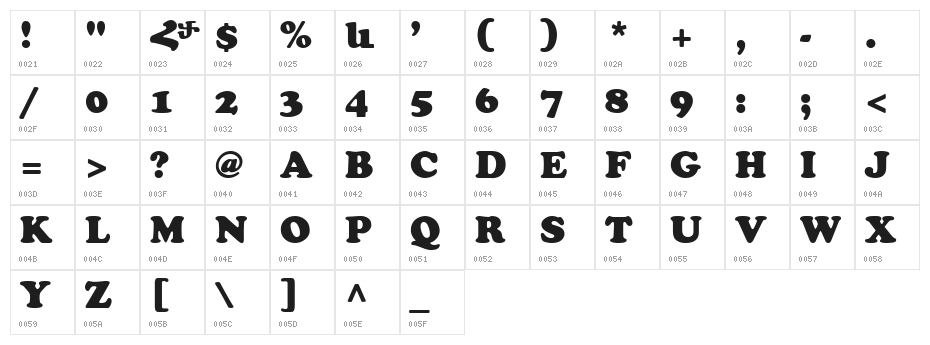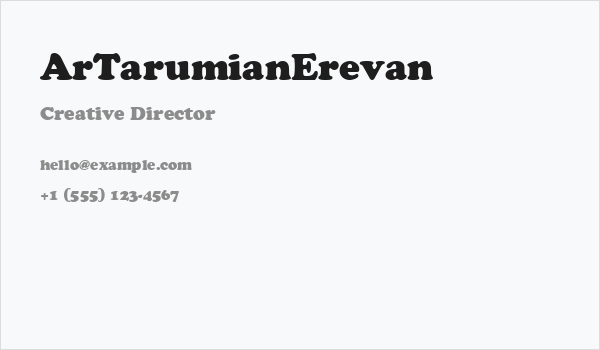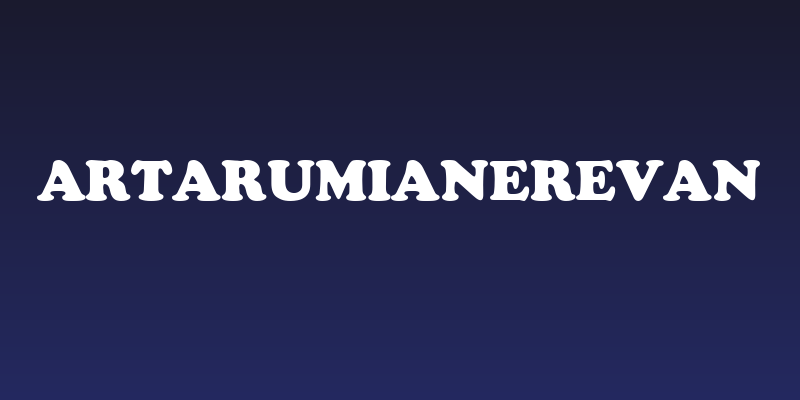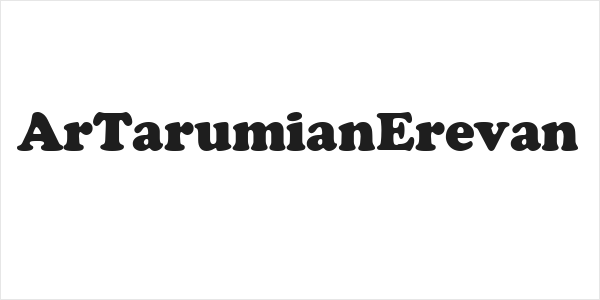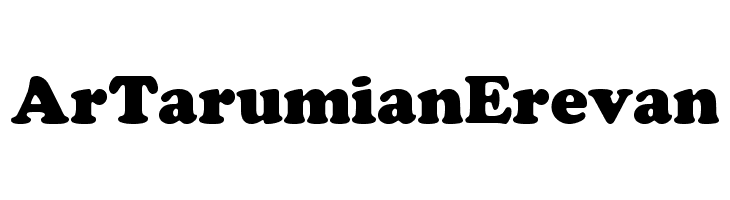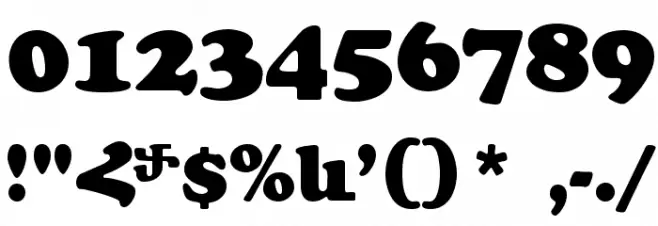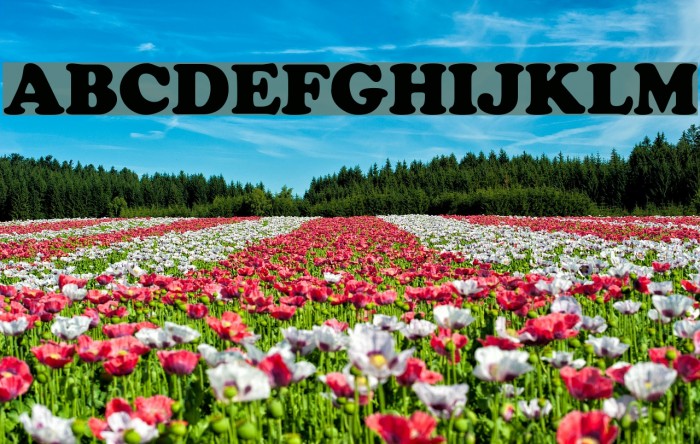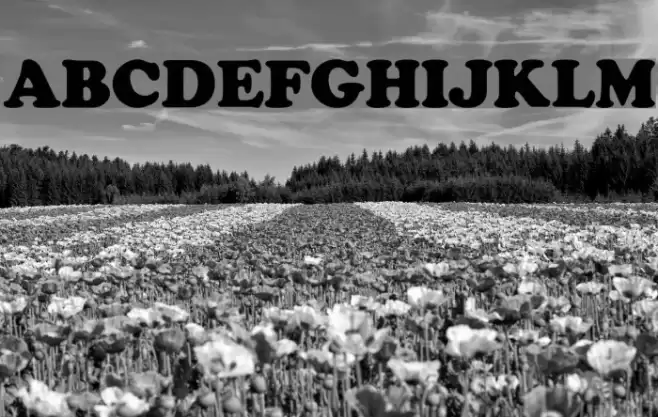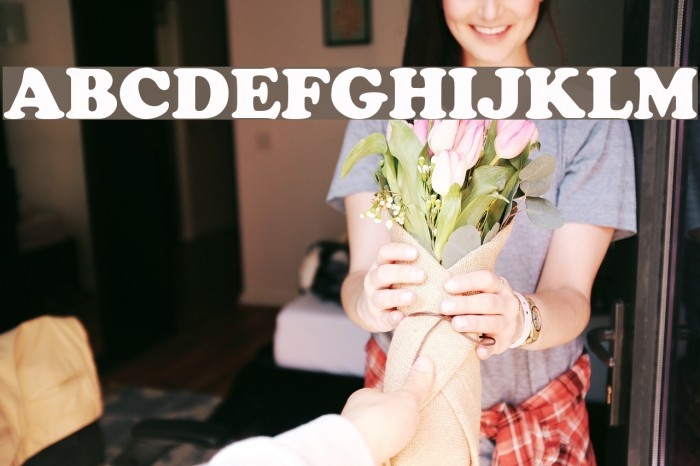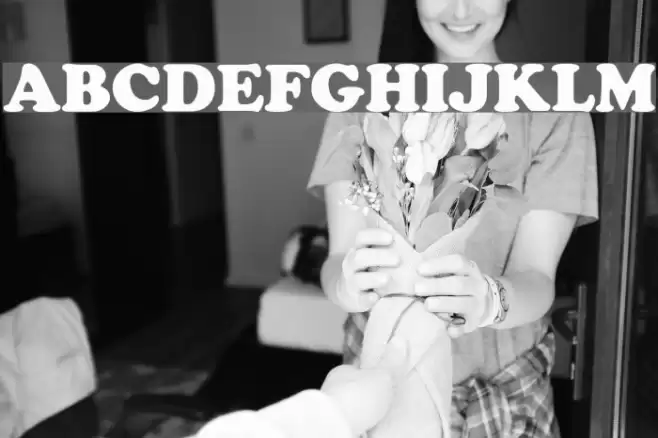
ArTarumianErevan Font
| Style général | Playful |
| Projets proposés | Ideal for children's books, playful branding, posters, and any design needing a fun and engaging typeface. |